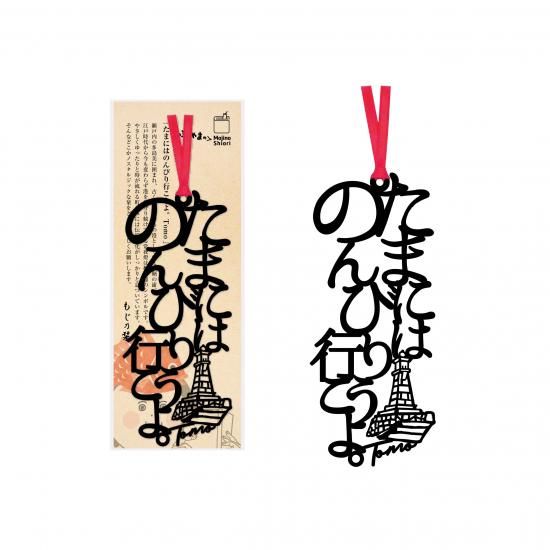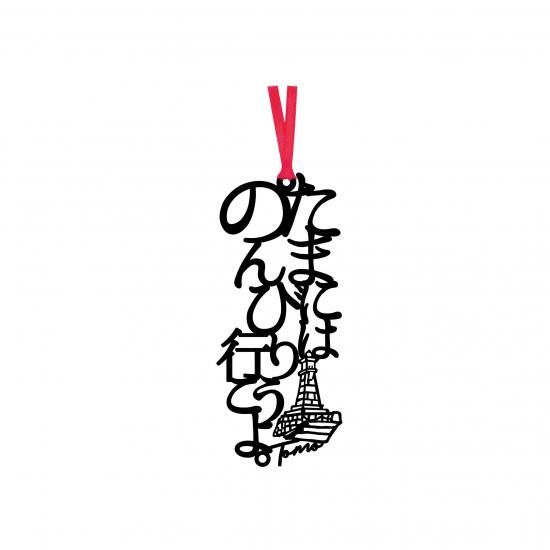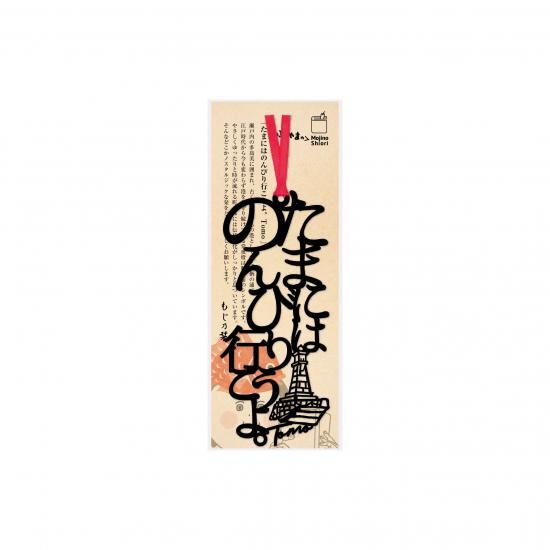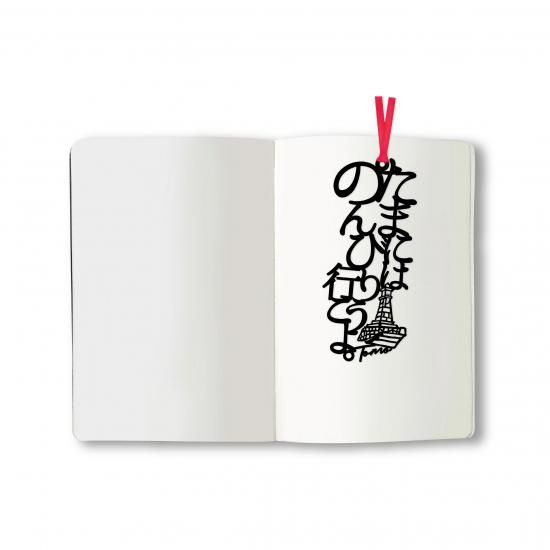
文字の福山のしおり「たまにはのんびり行こうよ。Tomo」
瀬戸内の多島美に囲まれ、古くから潮待ちの港として栄えた鞆の浦。
江戸時代から今も変わらず港を見守り続けている常夜燈は鞆の浦のシンボルです。
やさしくゆったりと時が流れる町並みには伝統文化がしっかりと息づいています。
そんなどこかノスタルジックな栞をどうぞよろしくお願いします。
木材パルプや綿を原料とした環境素材で、耐久性・耐水性に優れたファイバーの特徴を活かすことで、言葉がフォントごと切り取られたような巧緻で美しい『文字のしおり』のデザインが実現しています。